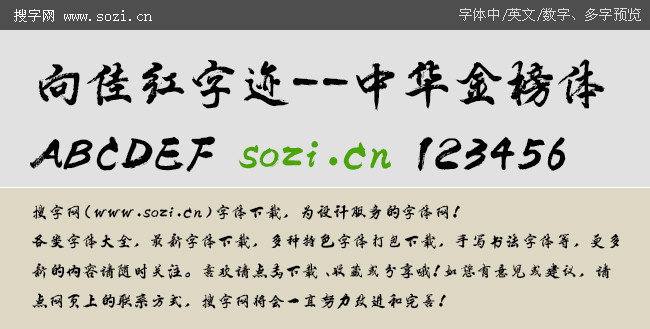
向佳紅字跡——中華金榜體
搜字網(wǎng)提供一款向佳紅字跡——中華金榜體中文字體下載,向佳紅字跡——中華金榜體是一款由書法家向紅佳先生制作的一款非常漂亮的書法字體。版權(quán)歸向佳紅先生本人所有,僅限學(xué)習(xí)、交流使用,成就展示,禁止商用及間接性盈利行為,個(gè)人作品對(duì)主動(dòng)征求合作的商業(yè)合作單位及個(gè)人象征性收取費(fèi)用,如需商用請(qǐng)聯(lián)系作者本人書面授權(quán),以免帶來不必要的糾紛,版權(quán)所有,違者必究。 【向佳紅老師聯(lián)系方式:電話(微信):15917354325 微博:https://weibo.com/u/2239015803】